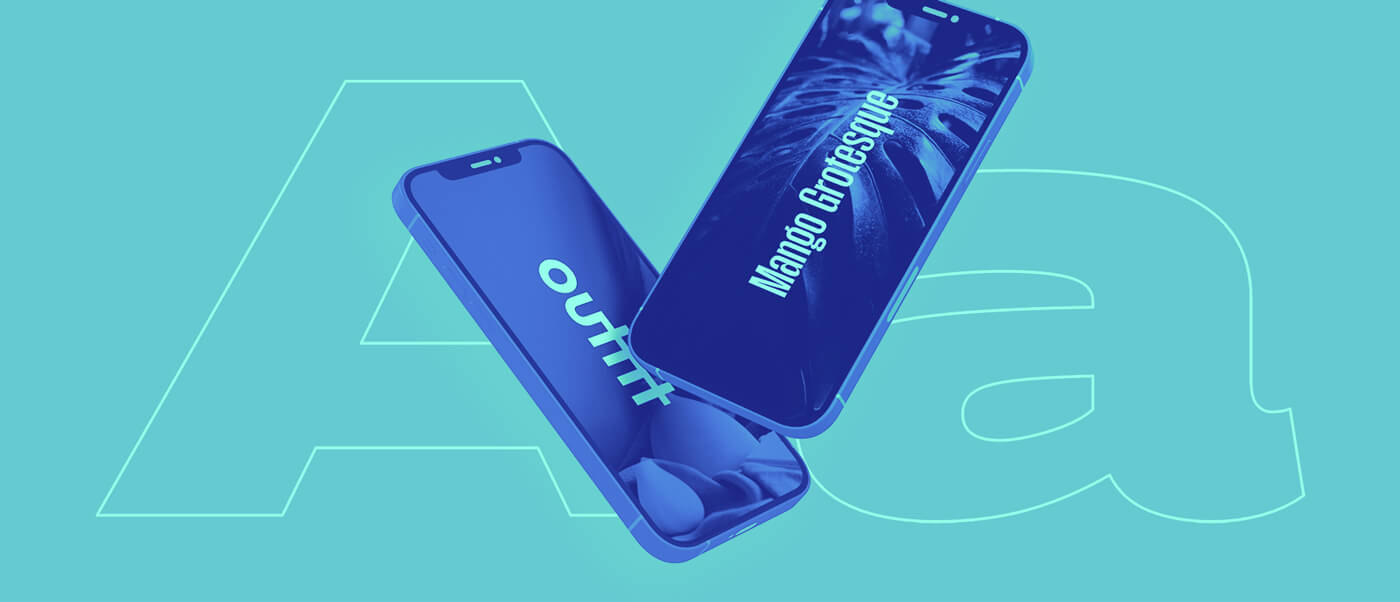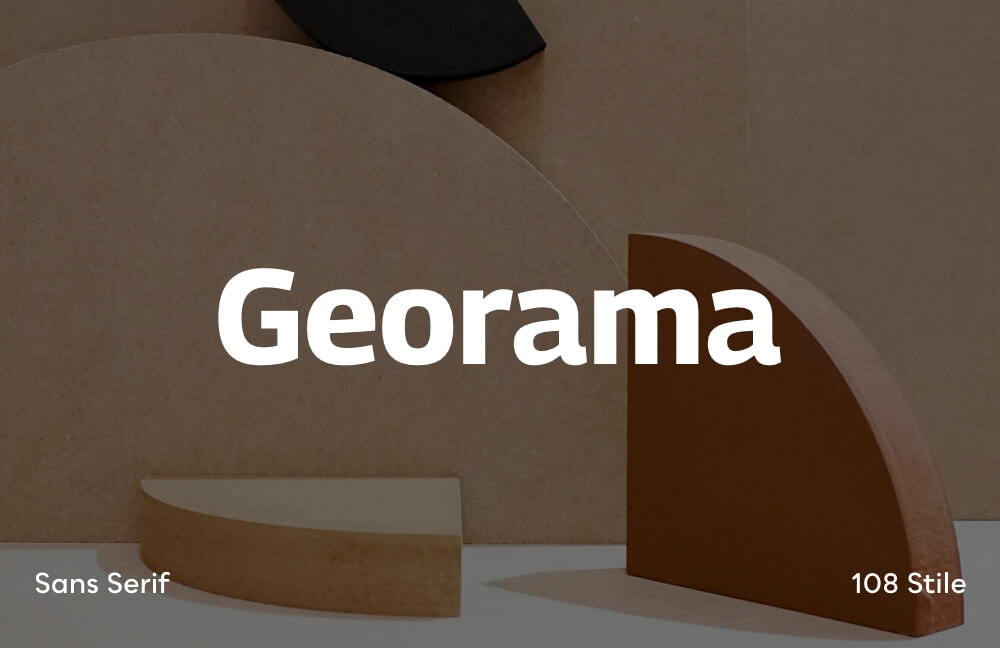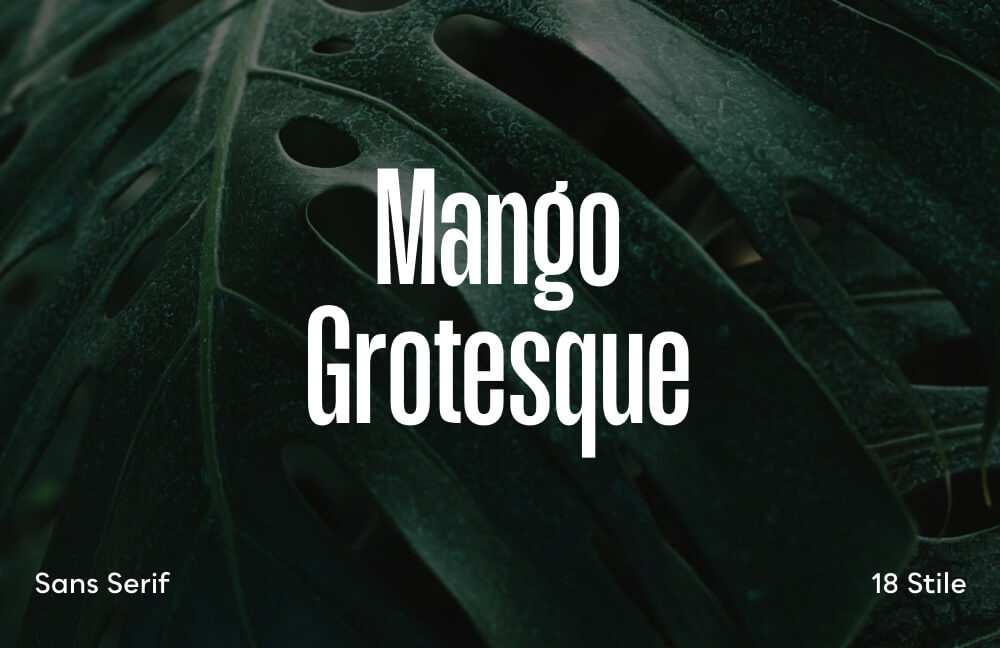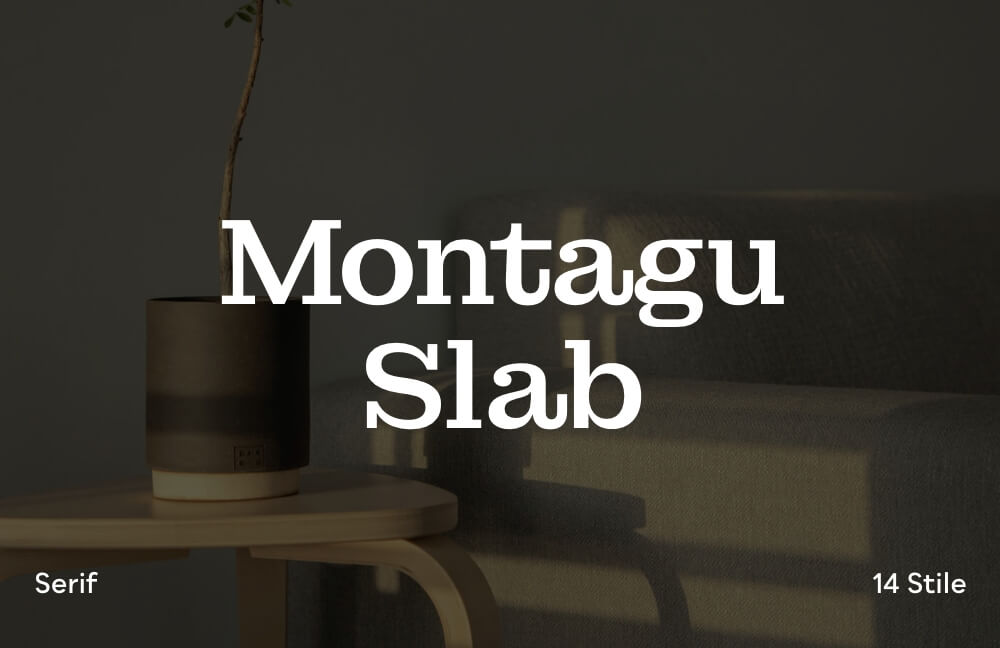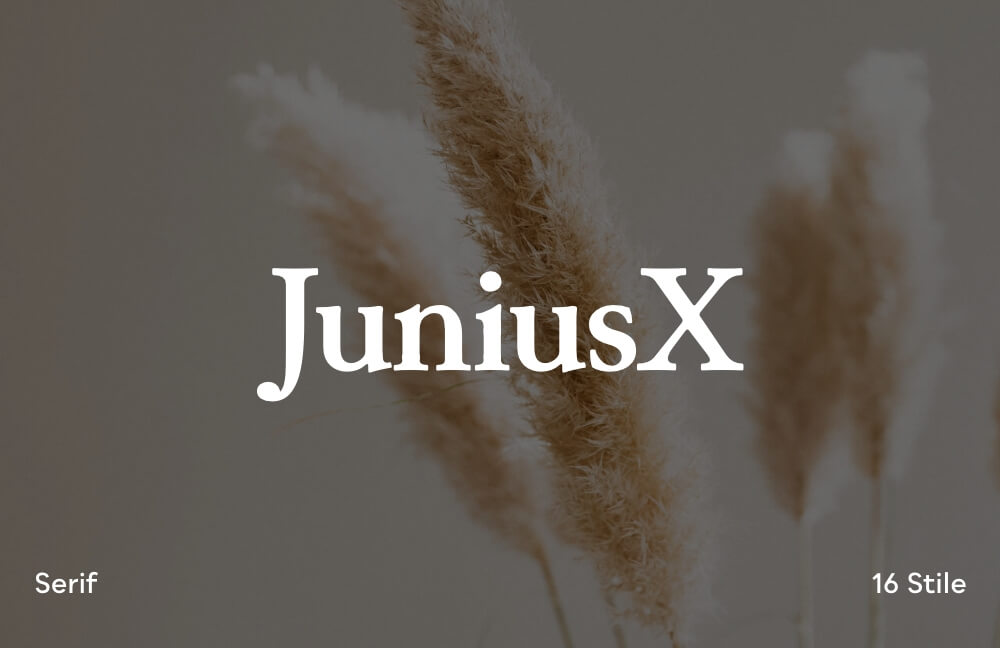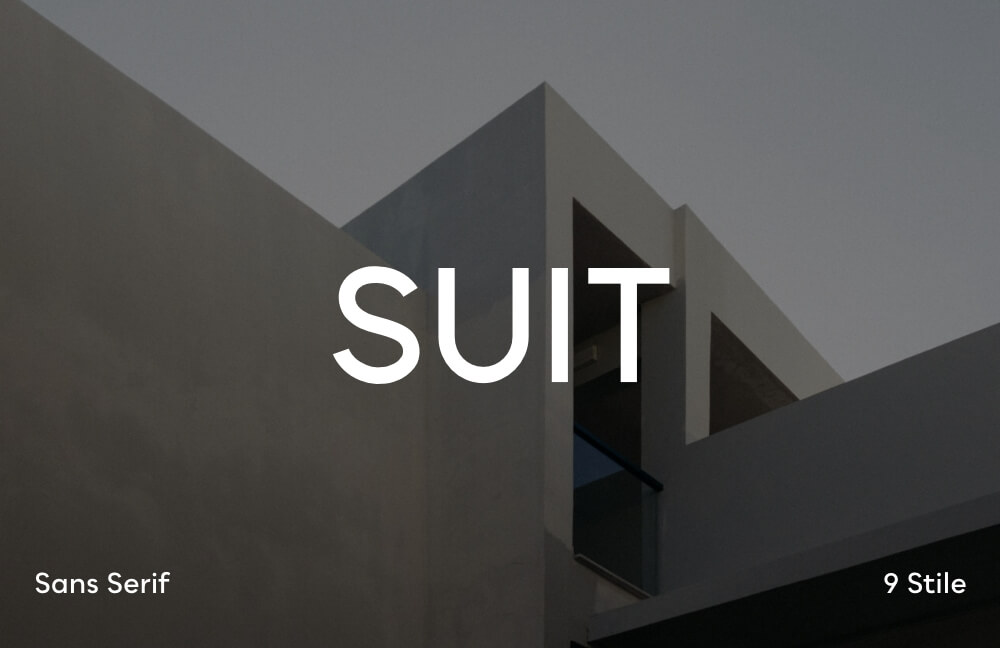
Variable Fonts – Potenzial im Webdesign + 9 kostenlose Beispiele
Was sind Variable Fonts? Das neue Schriftformat ermöglicht flexible Möglichkeiten und Vorteile für Fonts im Webdesign. 9 Kostenlose Beispiele für deine Website.
Zwei schwebende Smartphones zeigen Beispiele von Typography.
Schon einmal von Variablen Fonts gehört? Variable Fonts sind das neueste Schriftformat für Typography im Webdesign. In diesem Artikel werde erklären, wie das Schriftformat funktioniert, welche Vorteile es gibt und einige Beispiele von kostenlosen Variablen Fonts zum ausprobieren präsentieren.
Was sind Variable Fonts?
Variable Fonts nutzen CSS-Attribute um Schriftart, Schriftgewicht oder Schriftstile anzusteuern. Damit muss man bei der Gestaltung einer Website also nicht mehr mehrere Schriftarten einbetten, um den Schriftstil beispielsweise von „Light“ zu „Bold“ zu ändern. Das Gleiche gilt für Schriftbreiten wie „Condensed“ oder „Extended“.
Beim Verwenden von unterschiedlichen Schriftschnitten mussten die einzelnen Dateien separat eingebettet werden. Bevor die Schriftarten oder -schnitte auf dem Gerät eines Besuchers sichtbar wurden, mussten diese erst heruntergeladen und gerendert werden. Viele Schriftarten verlängern dadurch die Ladezeit einer Website und können vor allem das Nutzererlebnis beeinträchtigen.
Mit Variablen Fonts ist es möglich, mit nur einer Datei, die verschiedenen Gewichtungen und Stile zu erzeugen. Dabei gibt es einen Basisschriftschnitt. Durch die Steuerung von den Schriftachsen können so die unterschiedlichen Schriftstile dargestellt werden. Dadurch entstehen unbegrenzte Möglichkeiten zur Gestaltung durch Schriftarten, ohne die Ladezeit der Website negativ zu beeinflussen.
Ansicht der verschiedenen Achsen von Variablen Fonts.
Wie funktionieren Variable Fonts?
Die Funktion von Variablen Fonts lässt sich gut an der Schriftbreite erklären. Bisher lässt sich bei normalen Schriftschnitten die Schriftbreite nur wenig oder gar nicht ändern. Vor allem kann man sie nicht ändern, ohne die Qualität und das Design der Schrift zu beeinflussen. Für eine breiter laufende Schrift benötigt man also wieder eine eigene breitere Schriftart.
Bei einer Variablen Schriftart kann man die Schriftbreite mithilfe von CSS-Attributen steuern. Der Grad der Veränderung der Breite wird dabei mit einem numerischen Wert angesteuert. Der Große Vorteil dabei ist, dass das Grunddesign der Schriftart erhalten bleibt und die Schrift nicht „komisch“ oder „künstlich gequetscht“ aussieht. Mit dieser Funktionsweise lassen sich auch die Strichstärke, Kursivschrift, Neigung und optische Größe anpassen.
Variable Fonts Steuerung durch CSS-Tags.
Welche Vorteile haben Variable Fonts?
Wie oben schon erwähnt, bringen Variable Fonts einige Vorteile mit sich. Aus meiner Sicht gibt es 4 wichtige Gründe, warum es sich lohnt, Variable Fonts in einer Website zu verwenden:
• Schnellere Ladezeiten: Ohne das Einbinden von vielen einzelnen Schriftschnitten benötigt man weniger Datenmenge und Server-Ressourcen. Dadurch wird die Website schneller geladen. ‍
• ‍Verbesserte Benutzerfreundlichkeit: Durch die verbesserte Ladezeit verringert sich die Wahrscheinlichkeit, dass downloaden und rendern der Schriftart Verzögerungen für den User entstehen. Außerdem erhofft man sich mit dem neuen Schriftformat eine bessere Kompatibilität zwischen verschiedenen Betriebssystemen.‍
• Kreative Möglichkeiten: Für Designer ergeben sich durch die vielen Anpassungsmöglichkeiten mehr Möglichkeiten das jeweilige Design kreativ zu gestalten.
• Flexible Layouts: Variable Fonts sorgen für einen flexibleren Gestaltungsprozess, da man für Anpassungen von Schriftbreite oder Schriftgewicht keine neuen Schriftschnitte hochladen muss.
9 kostenlose Beispiele von Variable Fonts für deine Website:
Variable Schriftart Vorschau Georama.
Georama
• Sans Serif
• Verfügbare Schriftstile: 108
• Designed von: Production Type
Variable Schriftart Vorschau Mango Grotesque.
Mango Grotesque
• Sans Serif
• Verfügbare Schriftstile: 18
• Designed von: Rajesh Rajput
Variable Schriftart Vorschau Montagu Slab.
Montagu Slab
• Serif
• Verfügbare Schriftstile: 14
• Designed von: Florian Karsten
Variable Schriftart Vorschau outfit.
outfit
• Sans Serif
• Verfügbare Schriftstile: 9
• Designed von: Rodrigo Fuenzalida
Variable Schriftart Vorschau JuniusX.
JuniusX
• Serif
• Verfügbare Schriftstile: 16
• Designed von: Peter Baker
Variable Schriftart Vorschau SUIT.
SUIT
• Sans Serif
• Verfügbare Schriftstile: 108
• Designed von: SUNN
Variable Schriftart Vorschau Meshed Display.